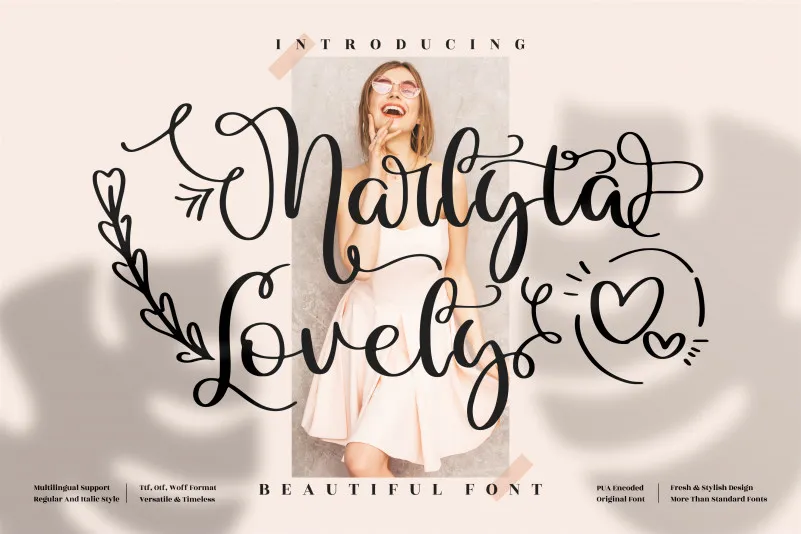
A Marlyta Lovely Font é uma fonte serif romântica que combina delicadas doodles e personagens, criando um estilo encantador que impressiona. É perfeitamente adequada para aplicativos como embalagens de produtos, frases, cartões de nome, rótulos, fotografias e muito mais. Esta fonte é PUA (Path User Area) codificada, o que significa que você pode acessar facilmente todos os caracteres e desenhos livres com facilidade. Para quem ama letras manuscritas, a Marlyta Lovely oferece uma paleta de opções sofisticadas e criativas. Ideal para personalizar um design específico ou criar identidades visuais memoráveis em diversas mídias. Seja você designer gráfico, fotógrafo ou simplesmente aquele que ama usar fontes originais na sua produção visual, a Marlyta Lovely Font é uma escolha certeira.